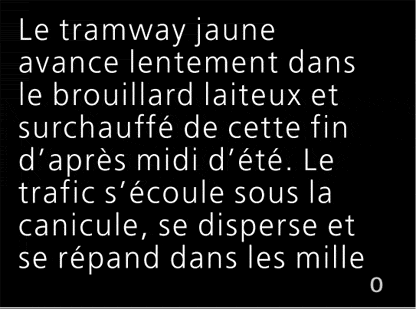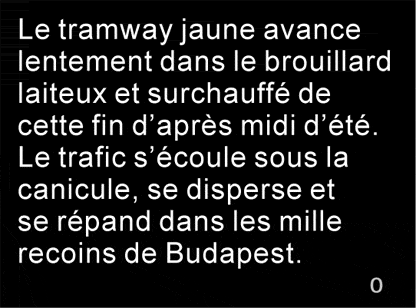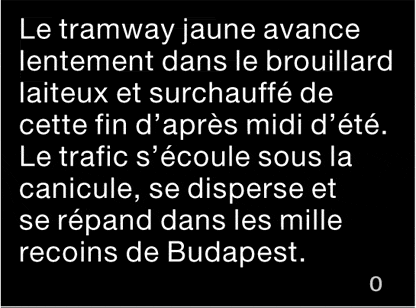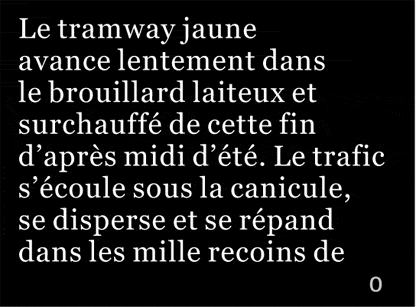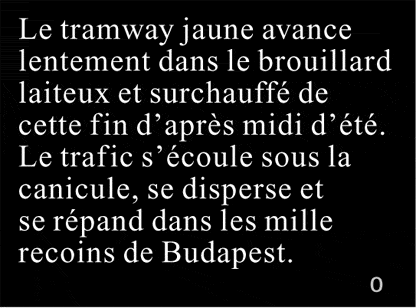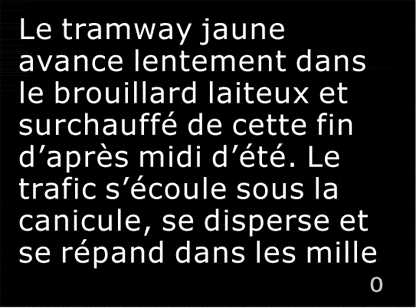
Voici un outil de travail et de réflexion, pour vous permettre de régler la typographie de vos websites ou blogs lorsque vous utilisez des fonds Noirs ou Couleurs foncées.
Je ferai l’ensemble de l’analyse comparative dans les jours qui viennent. Vous donne pour l’instant juste les paramètres techniques de ces figures, ainsi que l’adresse d’une galerie d’images qui synthétise toutes ces comparaisons.
Les chiffres en bas à droite de chaque rectangle correspondent à la tonalité des textes. 0 pour cent = blanc, 10,15,20… 88,91,94,97,100, au pourcentage de noir.
typo: Helvetica Neue 35 | vous demandez sans doute pourquoi j’ai pris les deux G du Franklin ITC Gothic, en exemple de contraste sur le fond noir. Question de Goût, comme je préfère également un News Gothic à un Helvetica, ou un Gill à un Futura, mais nous nageons dans des eaux troubles de la subjectivité. Juste une précision, je trouve que les caractères que je préfère ont tous un point commun, une souplesse due à la gravure, due à la main de l’ouvrier qui creuse le métal du poinçon en y ajoutant une part de son habileté manuelle pas trop mécanique. J’aime la calligraphie, les dessins à la main levée au pinceau, au calame, et l’on retrouve ces irrégularités dans un caractère comme celui d’Éric Gill. Quant à l’Helvetica, il est l’œuvre d’un «architecte» soucieux de la construction et des équilibres fondamentaux. Mais mon propos dans ce billet n’est pas tant de m’étendre sur mes états d’âme au regard d’une police ou d’une autre mais de souligner les différences de comportement des uns et des autres lorsque soumis au test «fatidique qui tue», je veux dire la composition d’une typo blanche sur fond noir.
AVERTISSEMENT:
Ces remarques et toutes celles qui vont suivre ne concernent que la chaîne éditoriale du web et non celui du Print et nous y reviendrons.
typo: ITC Franklin Gothic «Book»
typo: ITC Franklin Gothic «Heavy»
typo: Garamond Stempel «Regular»
typo: Trade Gothic N°18 «Condensed»
typo: Verdana «Regular» approches «0» (InDesign)
typo: Verdana «Regular» approches «+75» (InDesign)
Comparaison des polices Originales vs Polices «similar to»
typo Frutiger Light orignale
typo Verdana Regular (dessin de Mattew Carter d’après le Frutiger) pour Microsoft
typo Times New Roman Roman de Stanley Morison (Monotype Corp)
typo Georgia de Microsoft d’après le Times de Morison (dessin Mattew Carter). Il s’agit là d’un dessin spécialement conçu pour la lecture sur l’écran, on le voit notamment en examinant les empattements qi sont légèrement exgagérés pour supporter la lecture en c.9 sur un écran)
typo Helvetica Neue 55 de la fonderie Stempel
typo Arial (plagié par Monotype d’après l’Helvetica de Stempel pour éviter de devoir payer des droits)
Et maintenant je vous invite à découvrir les tableaux complets que j’ai élaboré afin de permettre une comparaison synoptique et à taille de lecture «normale» sur un écran. La galerie est ici. Encore une fois vous voudrez bien m’excuser de publier cette note en deux fois, retenez dores et déjà son permalien (permalink) et revenez y dans la semaine, je vous donnerai mes explications détaillées.